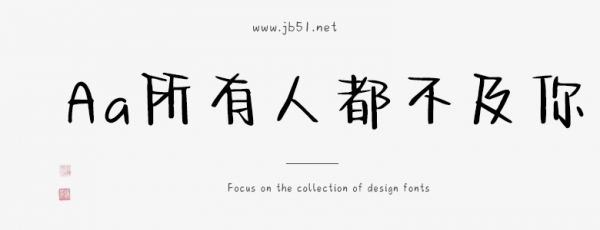
Aa所有人都不及你是一款不錯(cuò)的藝術(shù)字體,由Aa字庫出品,字體筆觸適中,書寫流暢,具有很好的視覺感,適合應(yīng)用于藝術(shù)設(shè)計(jì)、平面宣傳設(shè)計(jì)、網(wǎng)頁設(shè)計(jì),書法字帖等領(lǐng)域,需要的朋友可以前來本站下載。